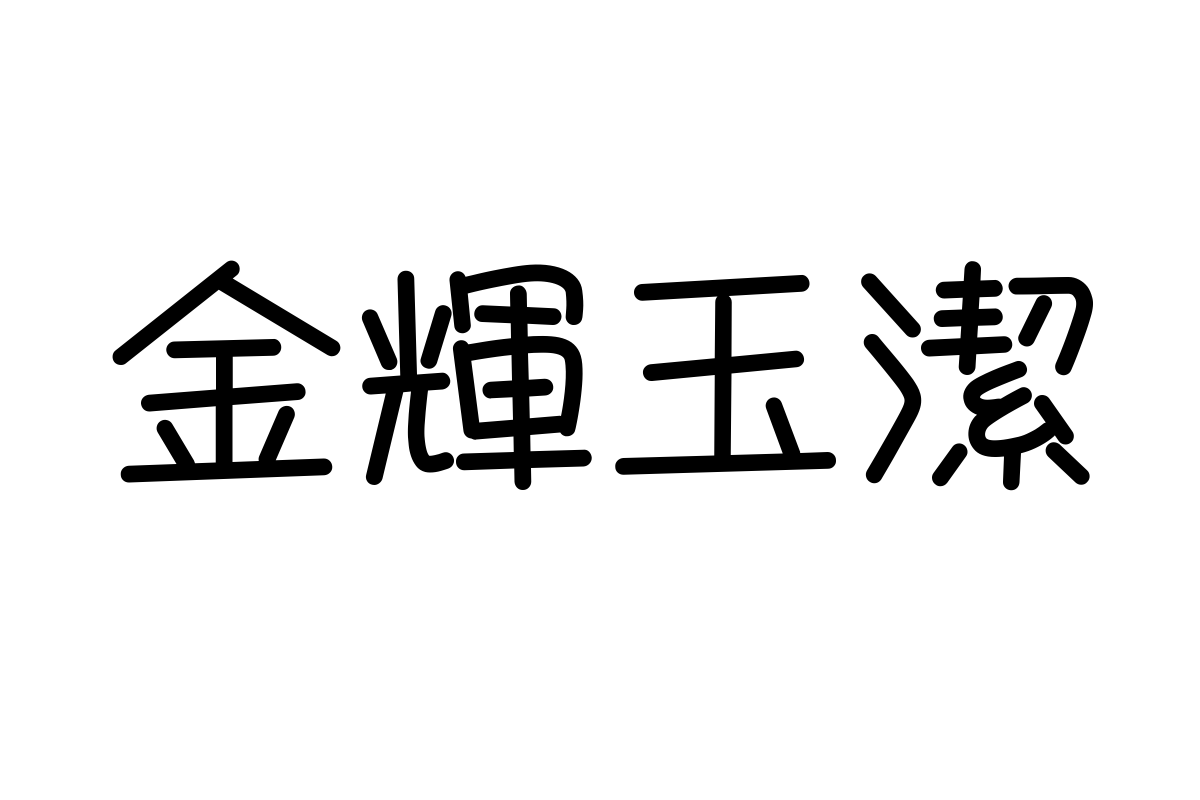
汉仪晴空体繁是一套具有现代感的中文字体,由汉仪公司设计。这套字体以其简洁、明快的特点而受到广泛欢迎。它适用于各种类型的文本,包括标题、正文、广告、包装等。
汉仪晴空体繁的特点是字形规整,笔画流畅,易于阅读和识别。它的线条粗细适中,既不过于粗犷,也不过于细弱,给人一种清晰、明了的感觉。同时,该字体还具有一定的可读性,即使在较小的字体下也能保持清晰。
此外,汉仪晴空体繁还注重细节的处理,如字间距、行间距等都经过精心调整,使得整体视觉效果更加和谐。这使得它在各种排版设计中都能展现出良好的效果。
总的来说,汉仪晴空体繁是一款适合现代商业、广告、出版等领域使用的字体。